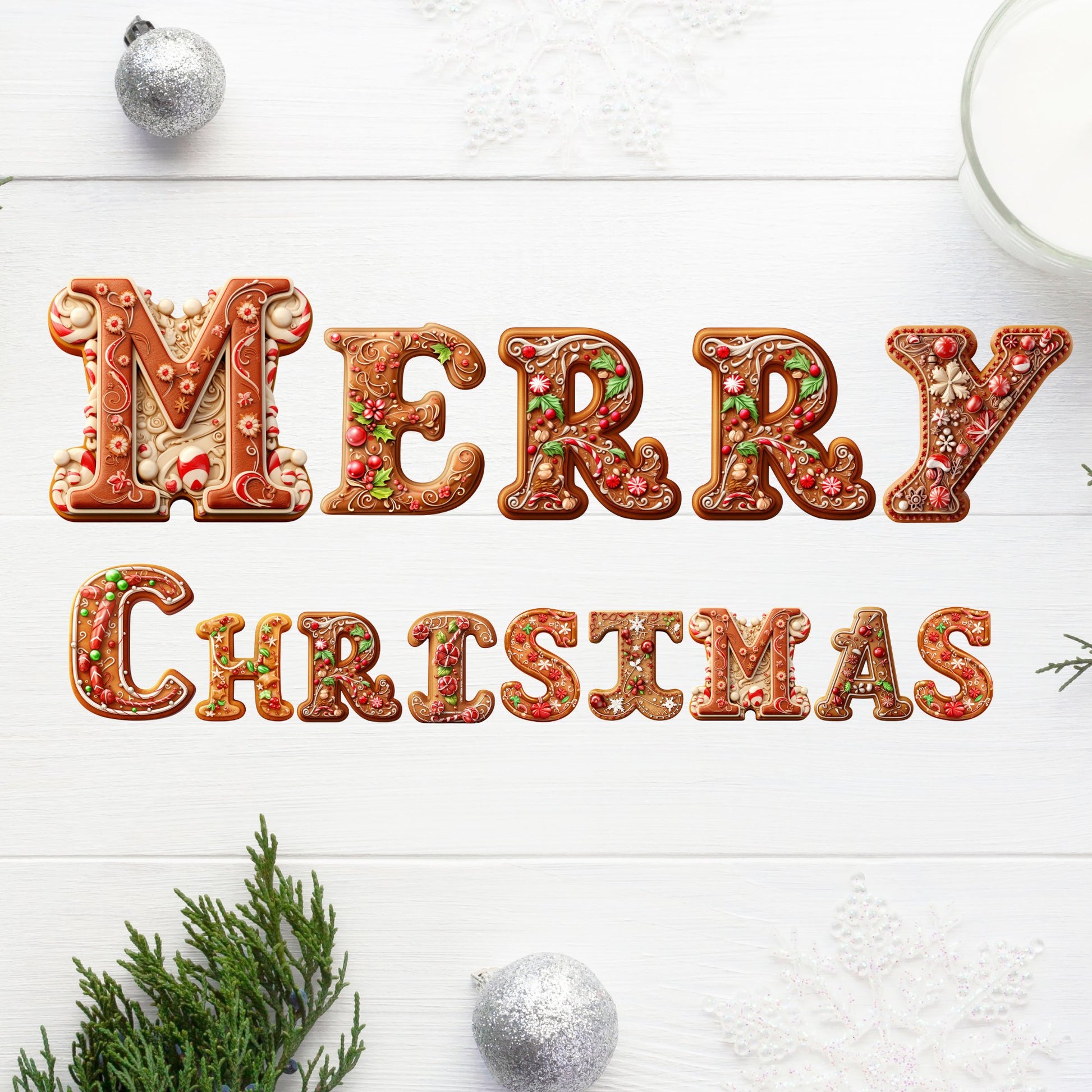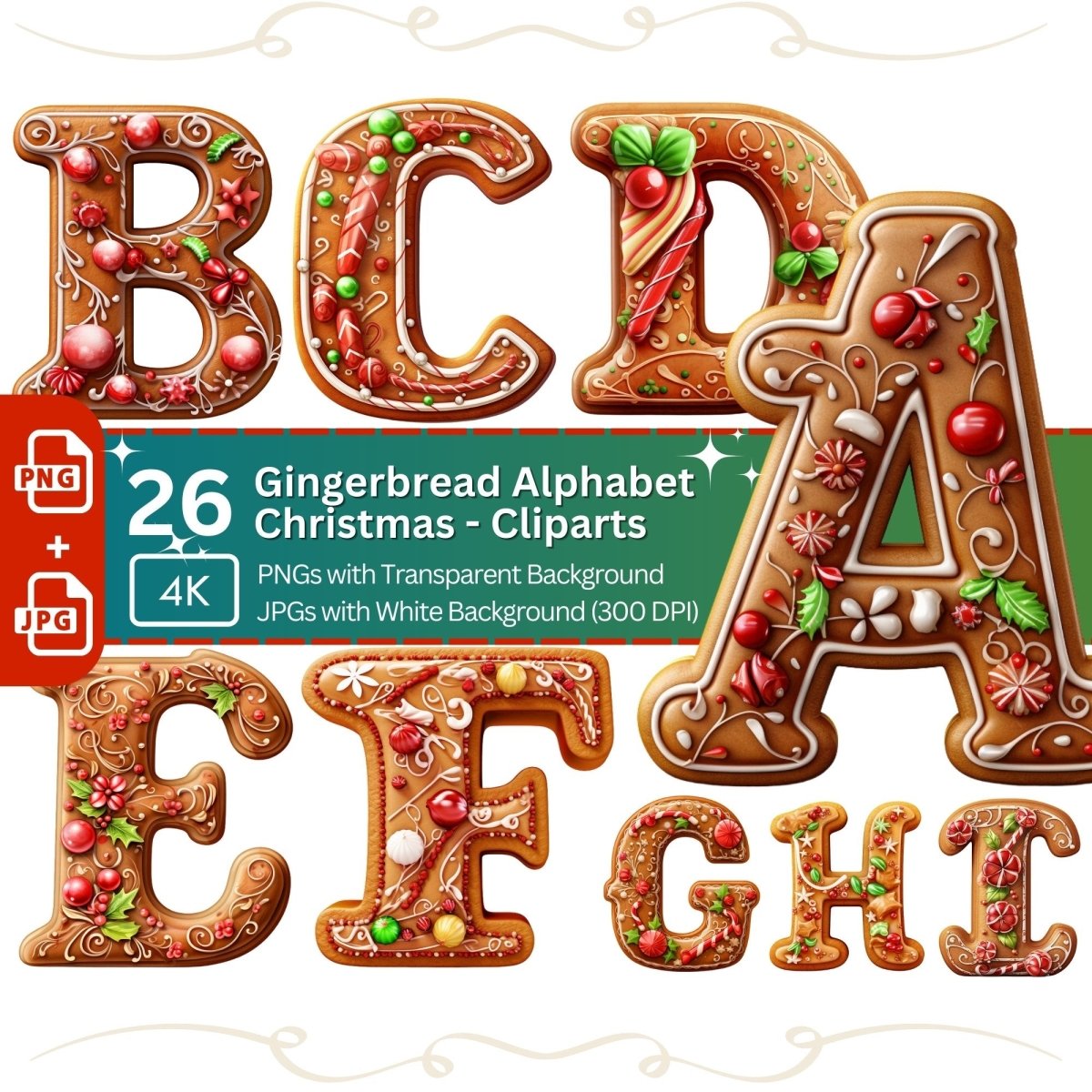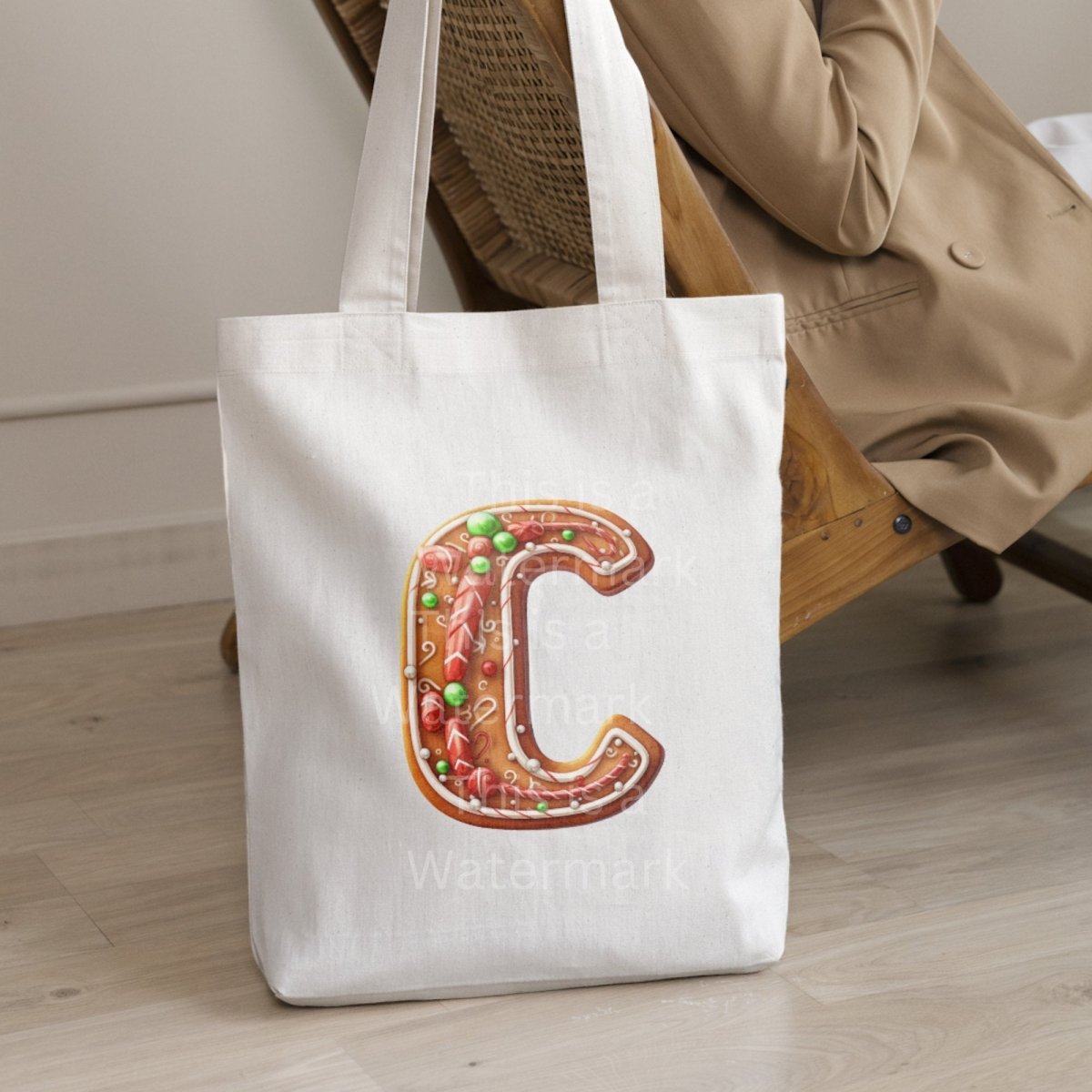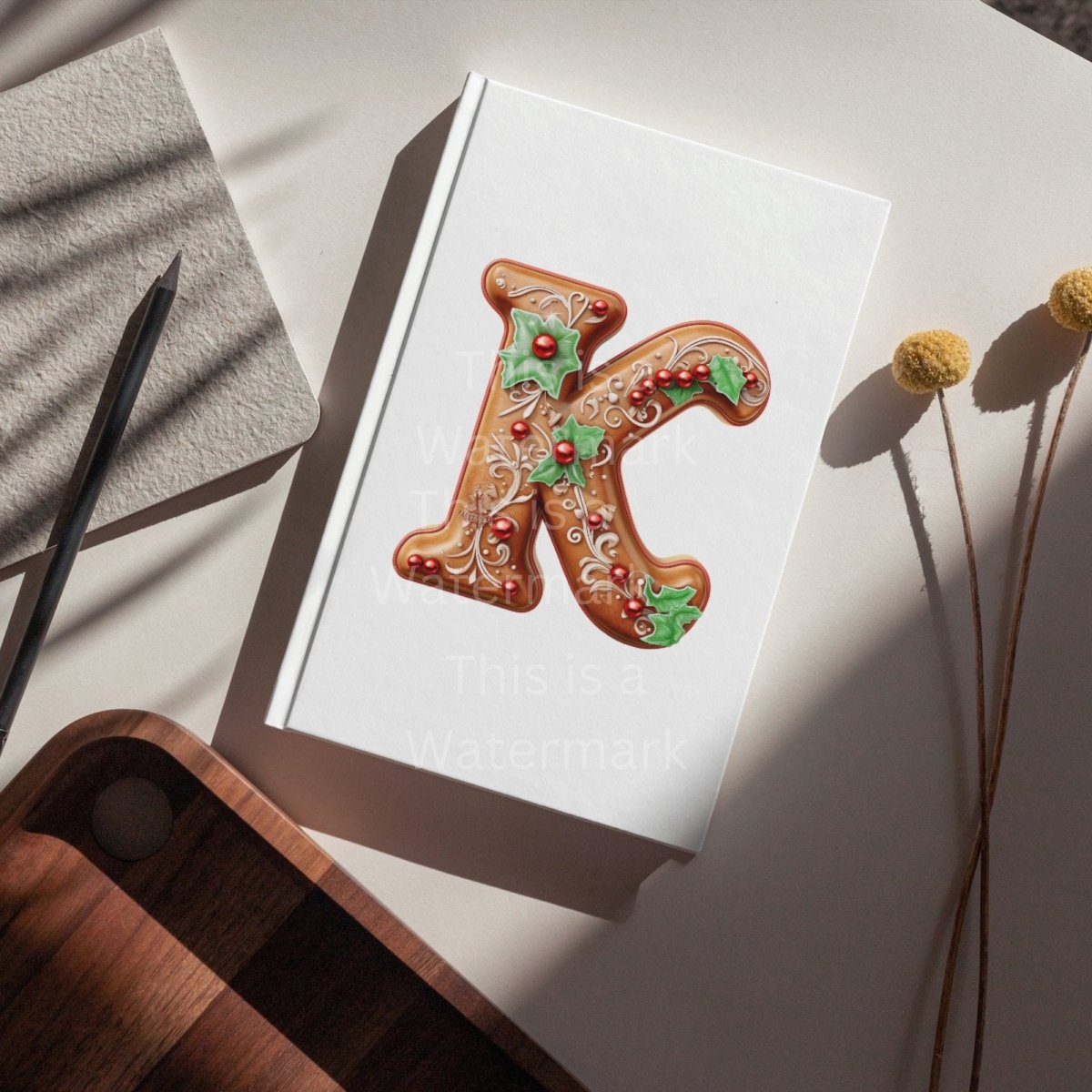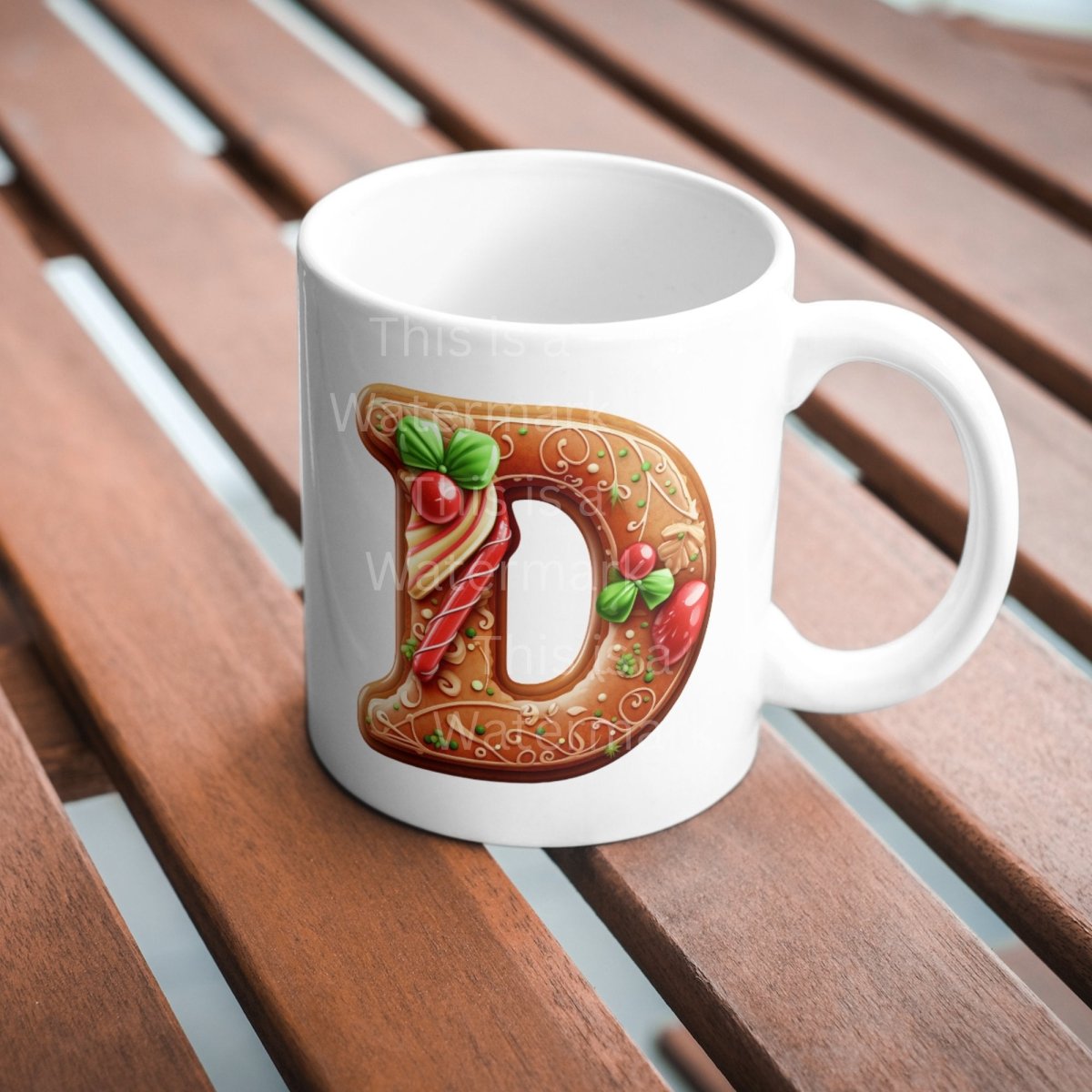
Lebkuchen-Alphabet 26 PNG-Clipart-Bundle, Weihnachts-Schriftart, Clipart, Kartengestaltung, Clip-Art, digitales Papierhandwerk, Feiertags-Buchstabengrafik
Das komplette englische Alphabet im Lebkuchen-Weihnachtsdesign. Perfekt für Weihnachtseinladungen oder -karten. Clipart PNG mit transparentem Hintergrund, außerdem 26 JPG-Dateien mit weißem Hintergrund.